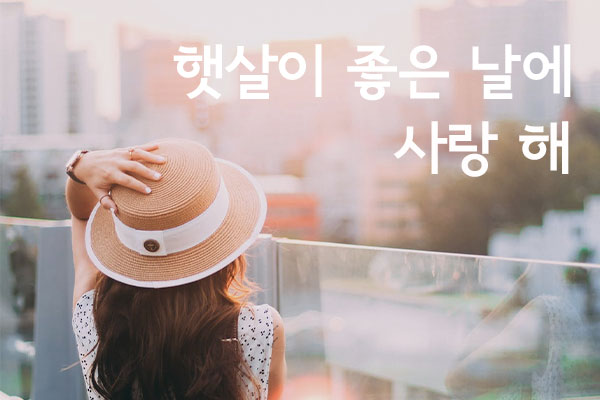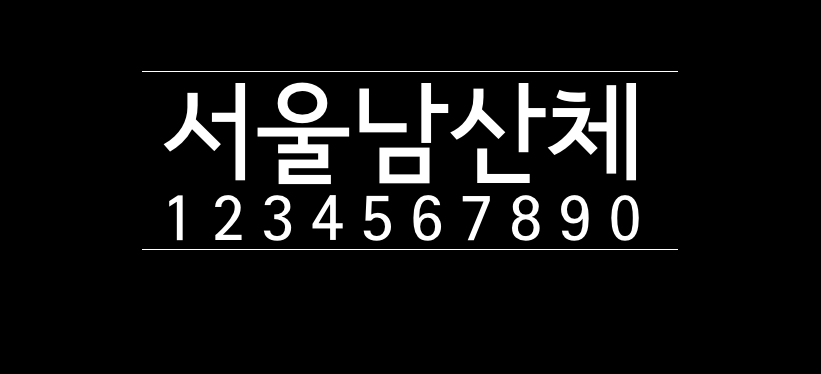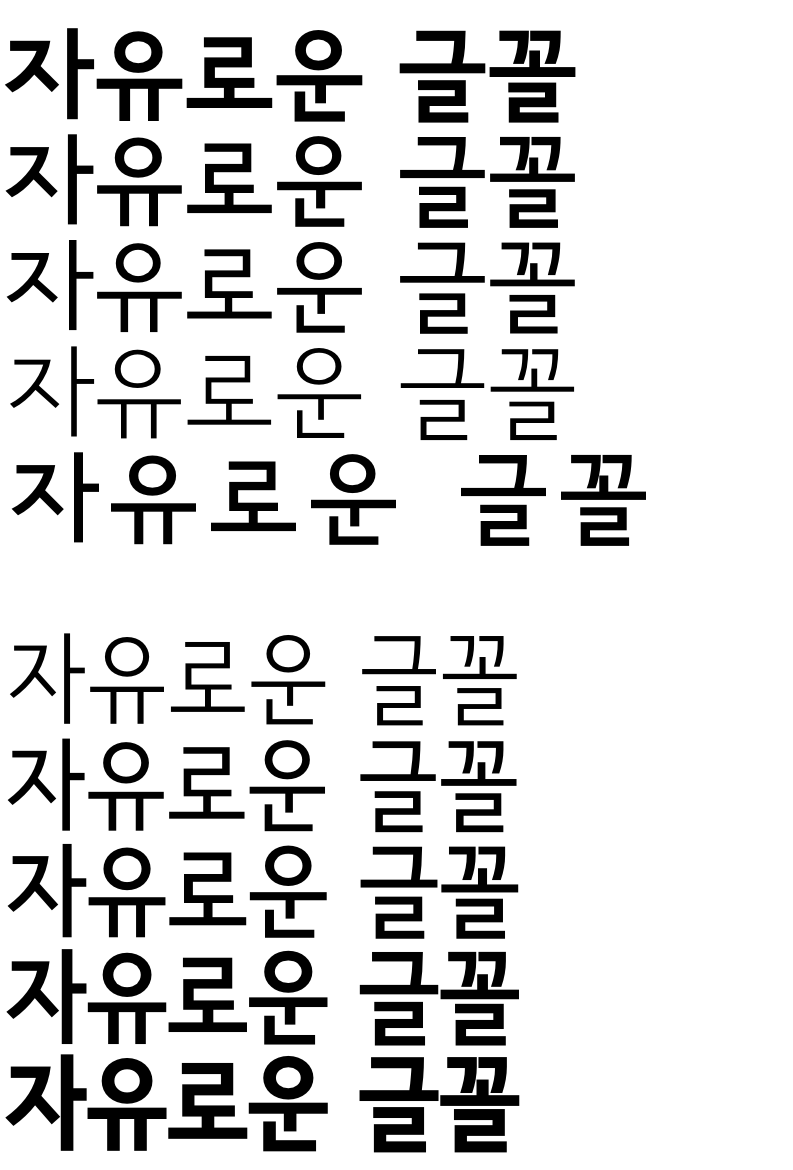
首尔南山体
首尔南山体(SeoulNamsan 、서울남산체)是由韩国首尔政府推出的,在首尔市为广泛使用的韩文字体,提升城市认同性与品牌价值而开发出首尔南山体。
首尔南山体通过不对称的“ㅅ”形,强调文字的动感,减少字幅,形成充裕的空间美,通过确保文字与文字之间的空间提高可视性,使用韩国式曲线表现其性质,通过底线变化提高可读性。
首尔南山体的笔画字形类似于国内的黑体字,该字体包含长体和正体两种风格,长体在纵向上比正体长一些,每种风格都包含5个字重,需要韩文字体的同学不要错过了!